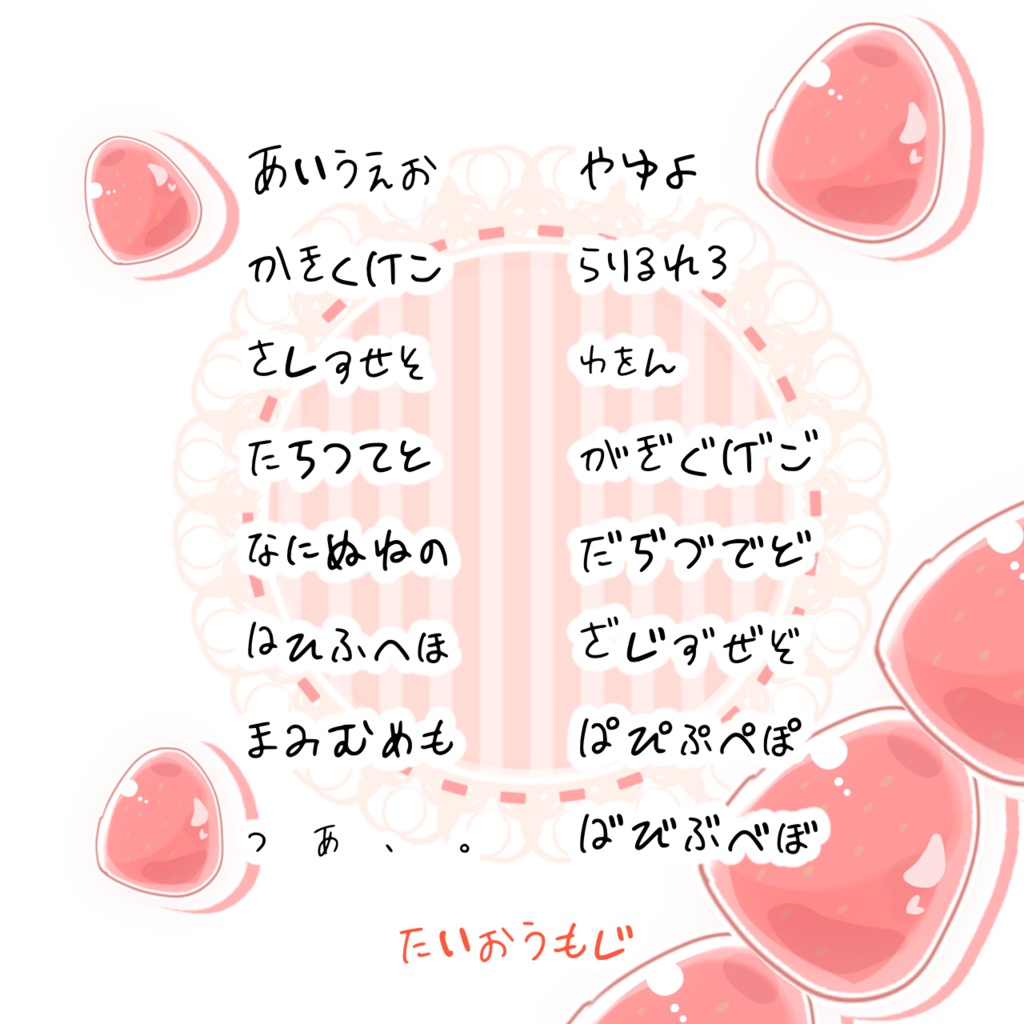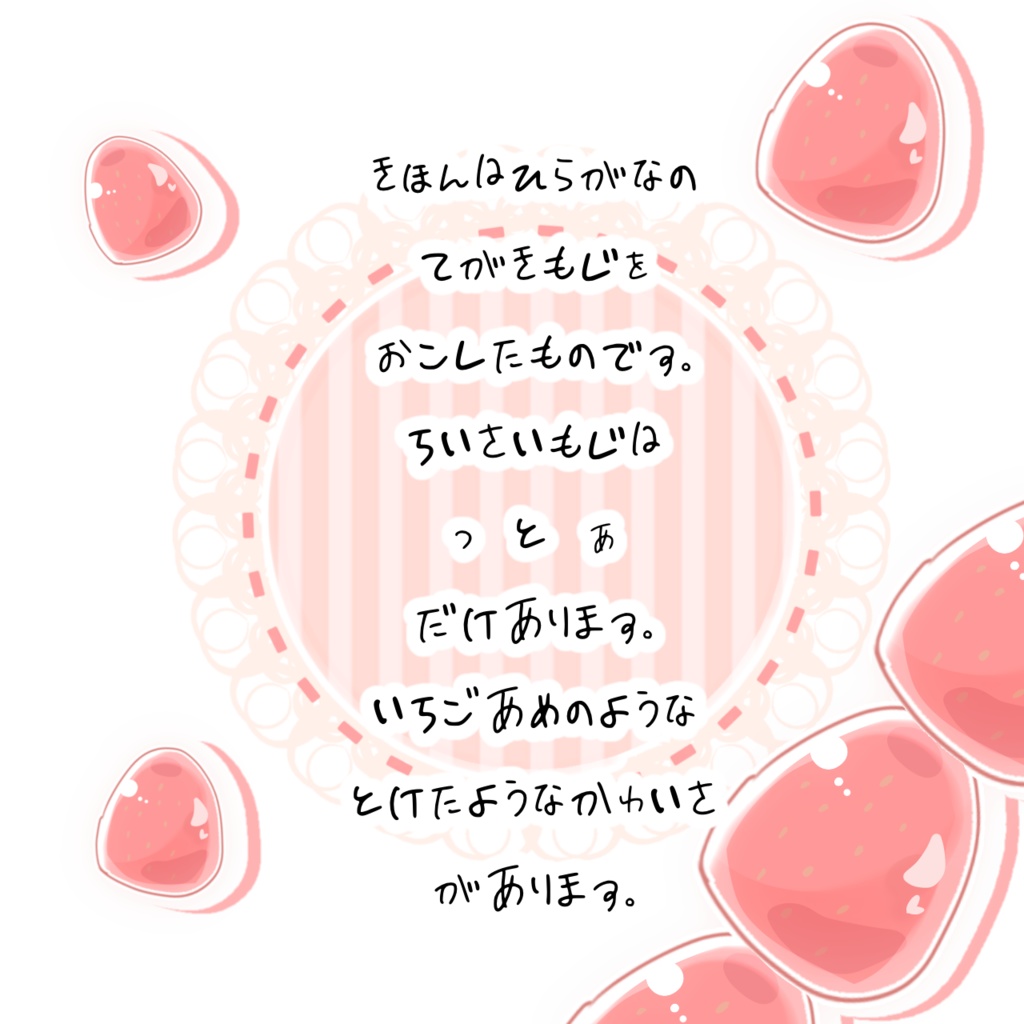
【フリーフォント】いちごあめフォント
【紹介】 ふぉろわーさんの手書き文字が可愛かったので許可を貰いフォントにしました。 フリーフォントになります。 基本自分用なので細かい荒さがある可能性があります。 いちごあめのようなコロコロした手書き感と丸っこさが特徴的です。 【対応文字】 ひらがなのみ ・小さい文字は「っ」と「ぁ」のみです。 ・がぎぐげごのような濁音、ぱぴぷぺぽも対応 ・記号は「、」「。」のみです。 ※小さいゃゅょなどはないので、画像作成環境(アイビスなど)であれば変形ツールなど使用で補えます。 【作成ツール】 Calligraphr( https://www.calligraphr.com/en/ )というサイトの75文字の無料版を使用しています。 ・形式はttfファイルです。 動作環境としては アイビスペイント Windows10のPC のみで確認しています。 他の動作確認は行っていませんのでご了承ください。 4~6枚目はiPhoneにおけるアイビスペイントへの導入の仕方です。 【使用可能】 ・基本フリーフォントになりますのでご自由にご利用頂けます。(文字を書いたフォロワーさんには許可いただいております。) ・創作などのフォントとしてお使いください。 ・使用報告、クレジット等は不要です。 【禁止用途】 ・データそのものの二次販売/二次配布 ・変形/加工等をしての二次販売/二次配布 ・個人問わず誹謗中傷や創作以外での反社会的使用 ・自作発言はご遠慮ください。 ・著作権の放棄はしておりません。 ★こちらのフォントを使用した上で起きた問題やトラブルに関して、こちらは何があっても一切の責任を負いません。 ・フォントデータのダウンロードした際に、これらの禁止事項に同意をしたものとみなします。 ・使用目的やその他ご不明点ございましたら、作成者のTwitterもしくはBOOTHのメッセージに反応頂けますと、素早いお返事が可能だと思います。 ※文字を提供して下さったフォロワー様への直接のご連絡は必ずお控えください。